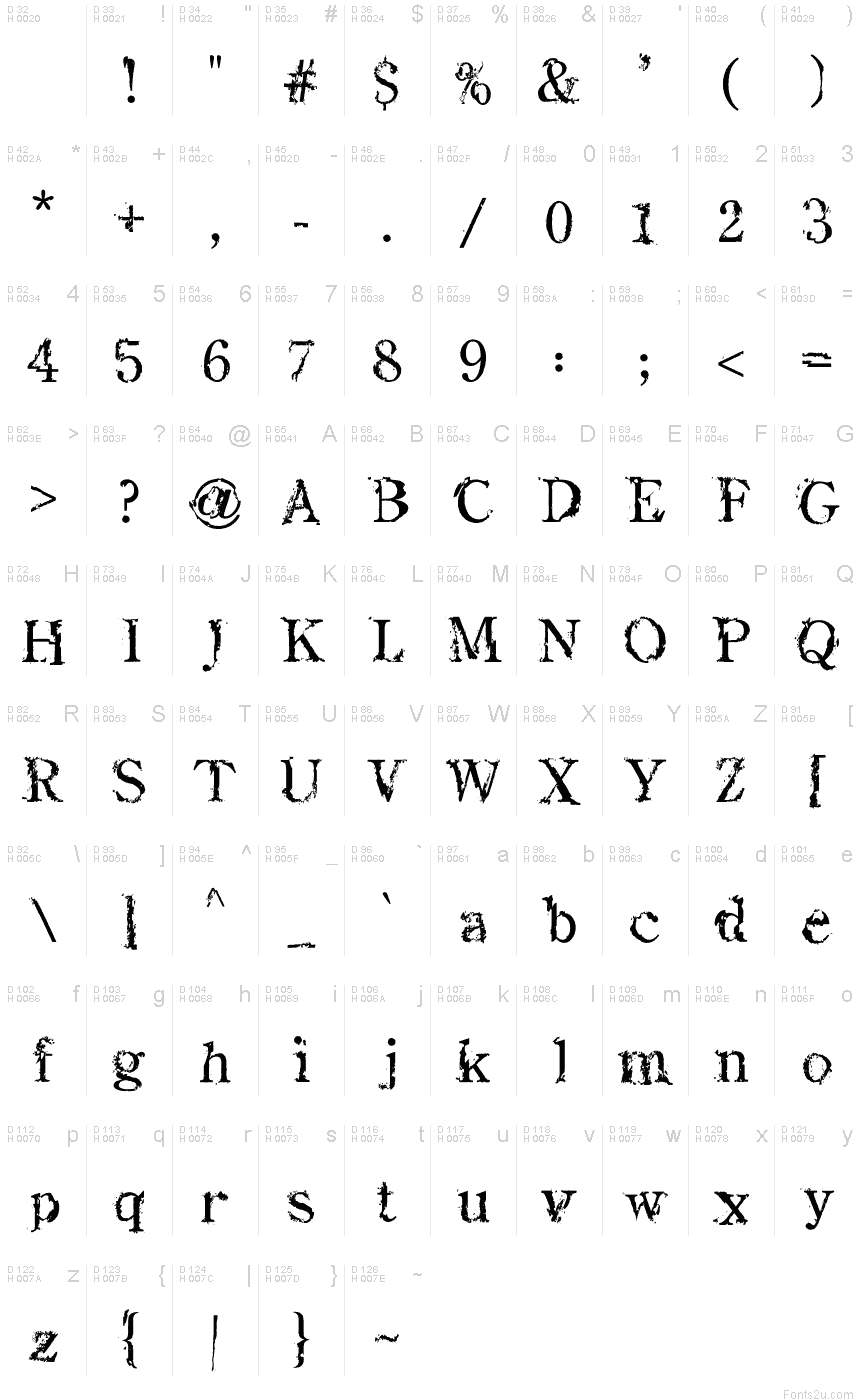
Sea Dreams to darmowy, erodowany krój typu display autorstwa Heather Taylor, stworzony w 2008 roku, o surowym, zniszczonym przez warunki atmosferyczne charakterze. Poszarpane krawędzie, rozproszone ubytki i nierówne, przypominające tusz plamy nadają literom wygląd starego druku, uszkodzonego przez sól, piasek lub lata użytkowania.
Jego popękana tekstura tworzy natychmiastowe wrażenie rozkładu na okładkach albumów i plakatach imprezowych, jednocześnie wprowadzając niepokojący klimat do horrorowych napisów tytułowych. Wykorzystaj ten darmowy font na opakowaniach napojów rzemieślniczych, okładkach redakcyjnych lub w identyfikacjach wizualnych marek z efektem starzenia, gdzie zniszczone liternictwo może współgrać z fotografią i teksturą materiałów, zamiast wyglądać jak czysta, cyfrowa nakładka.